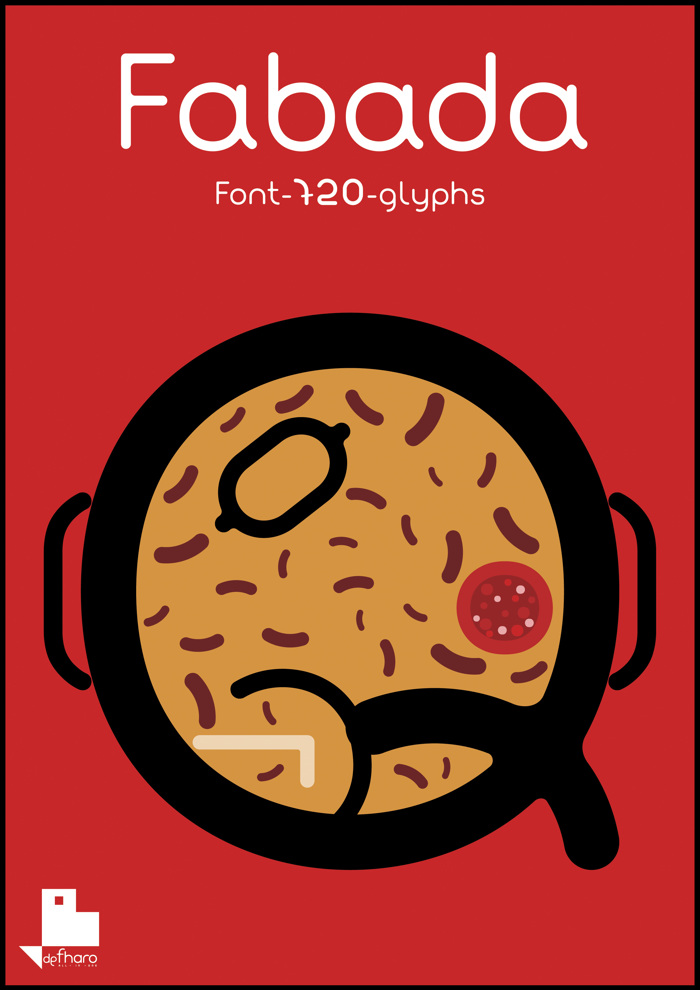
Fabada Font
Esta fue mi primera tipografía, está completa para los idiomas europeos derivados del latín. Es una fuente de inspiración retro, visita mi web para descargar otras fuentes.
This was my first typeface, is complete for European languages derived from Latin. It's a retro inspiration, visit my site to download other fonts.